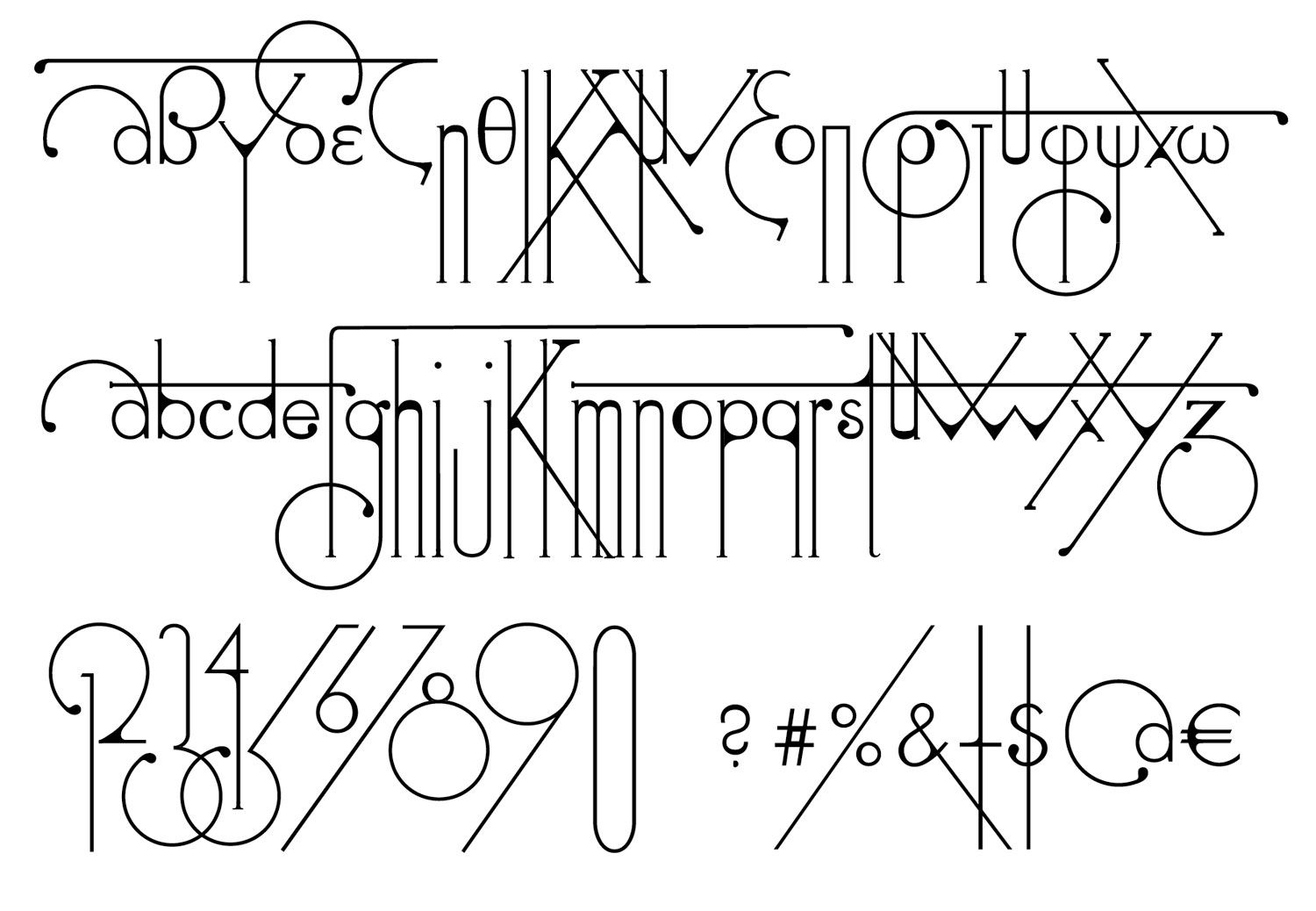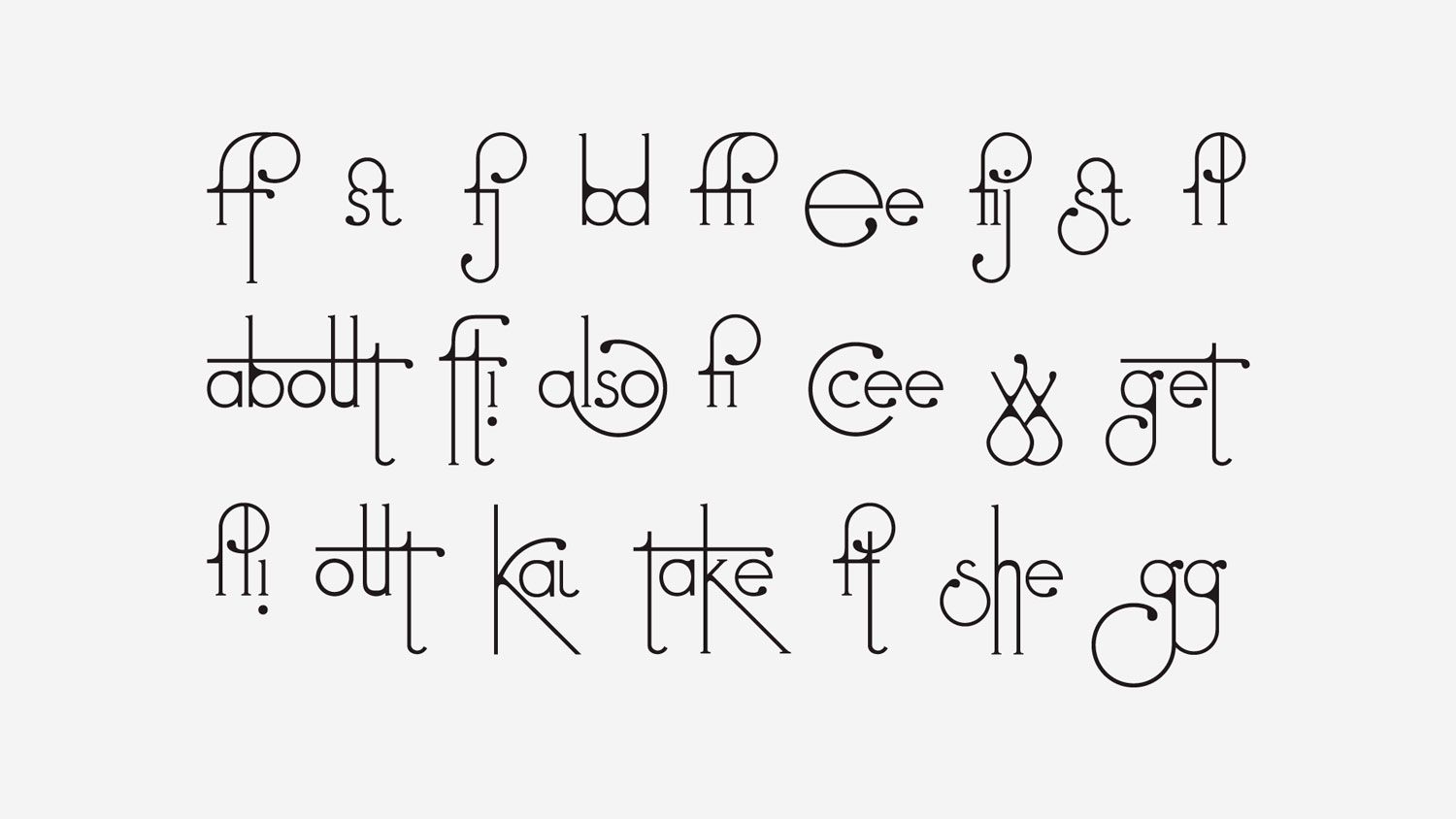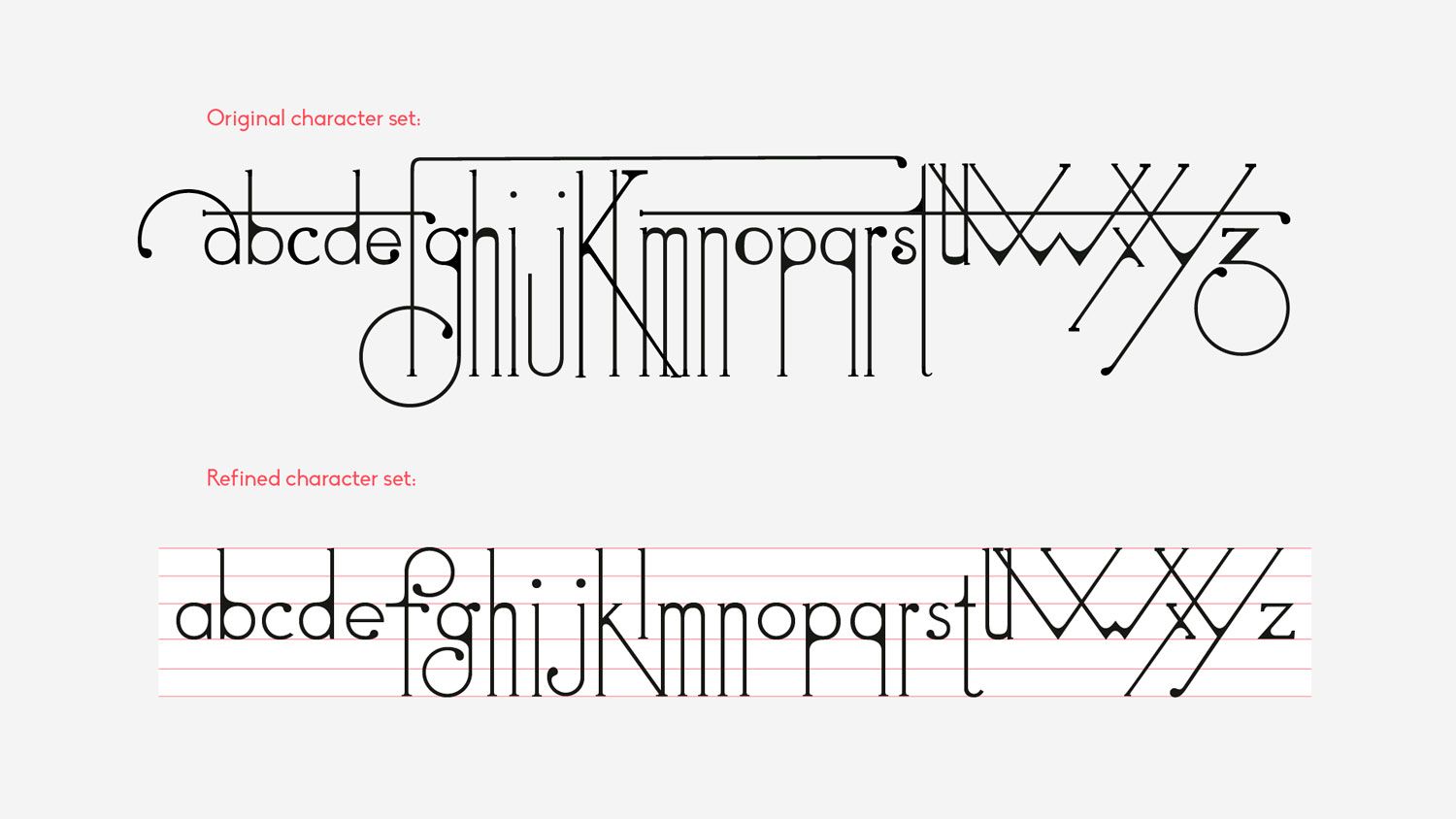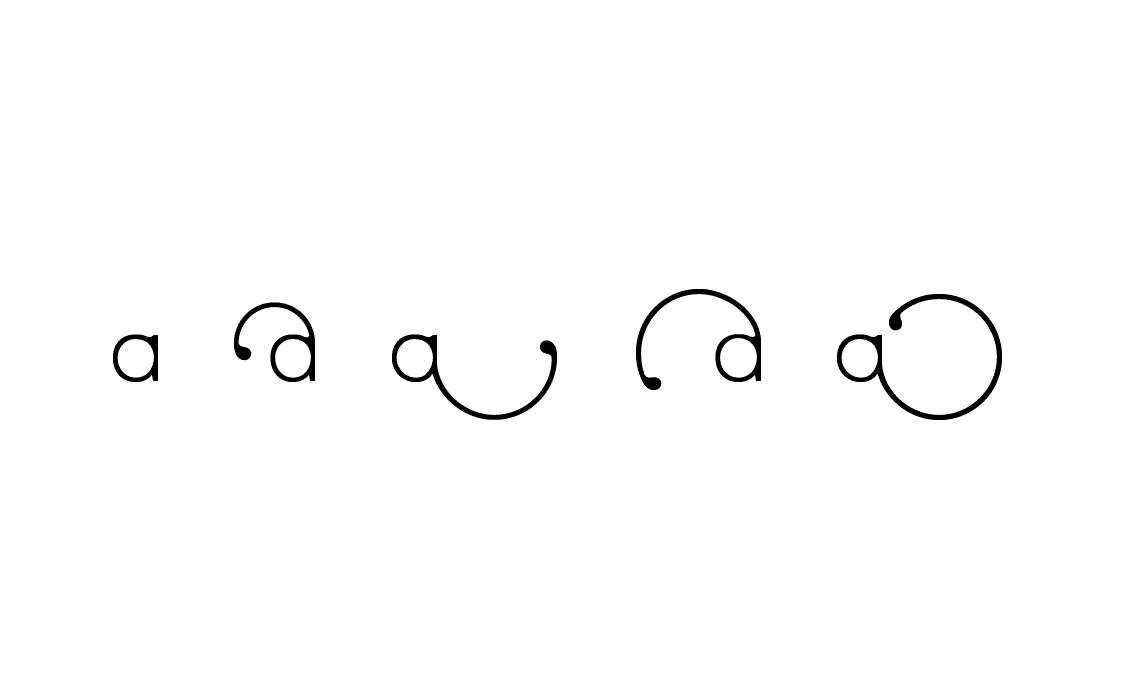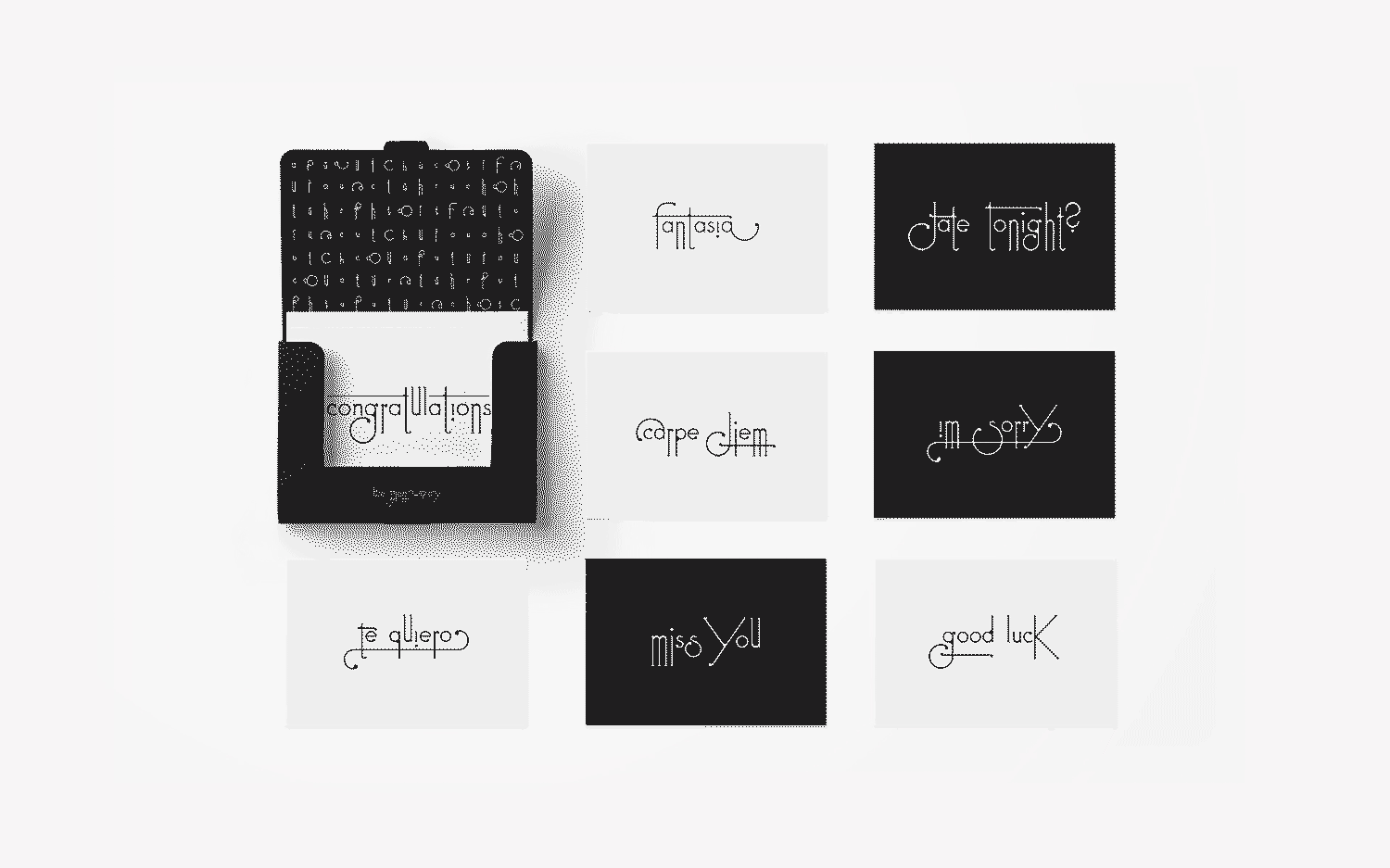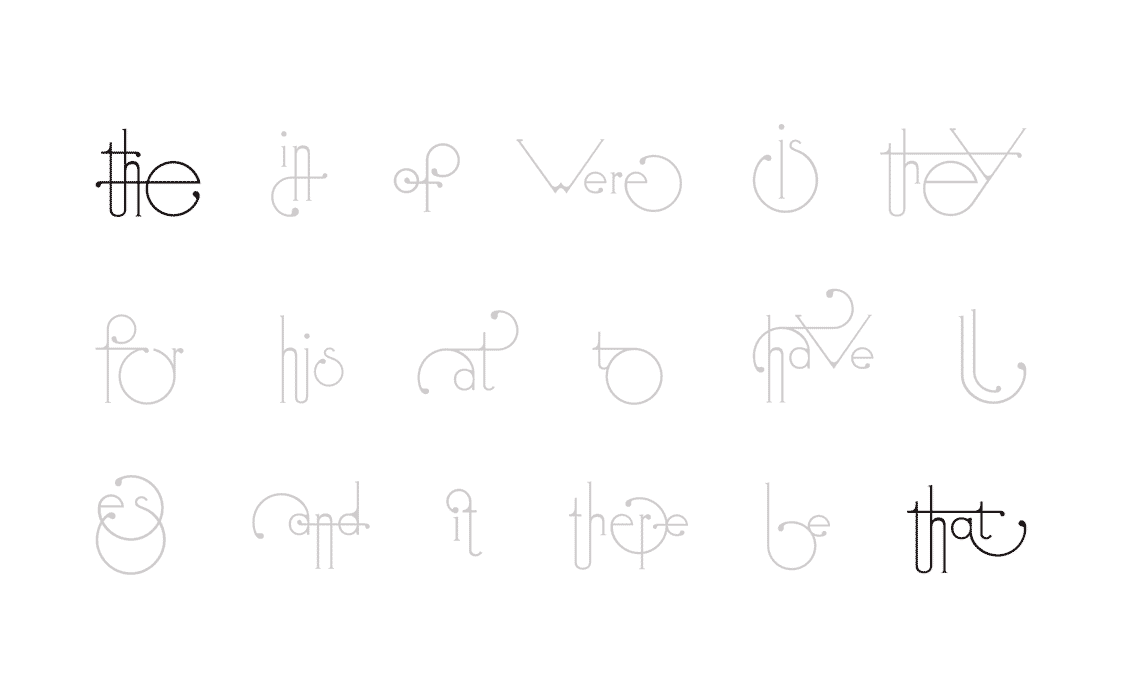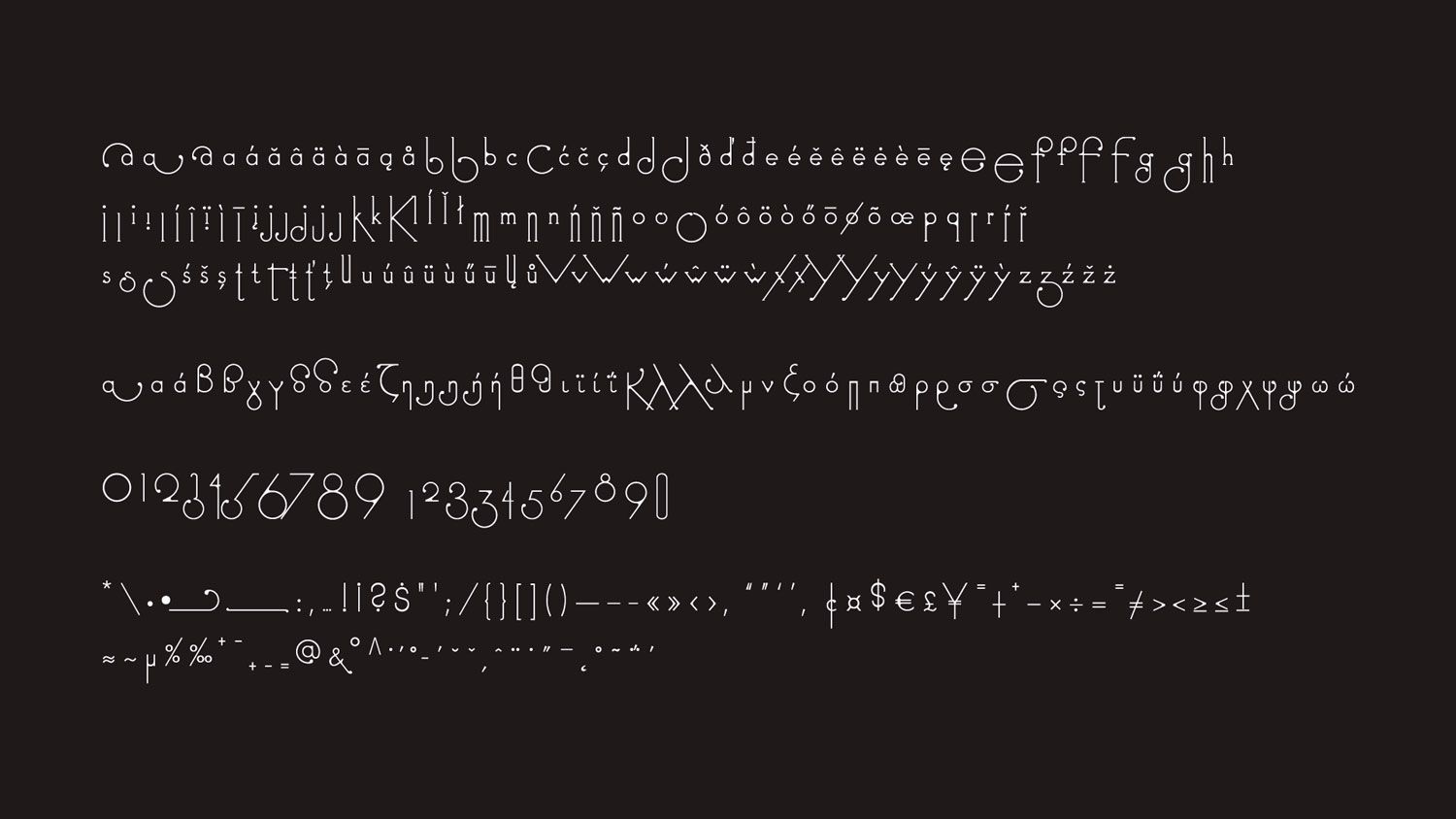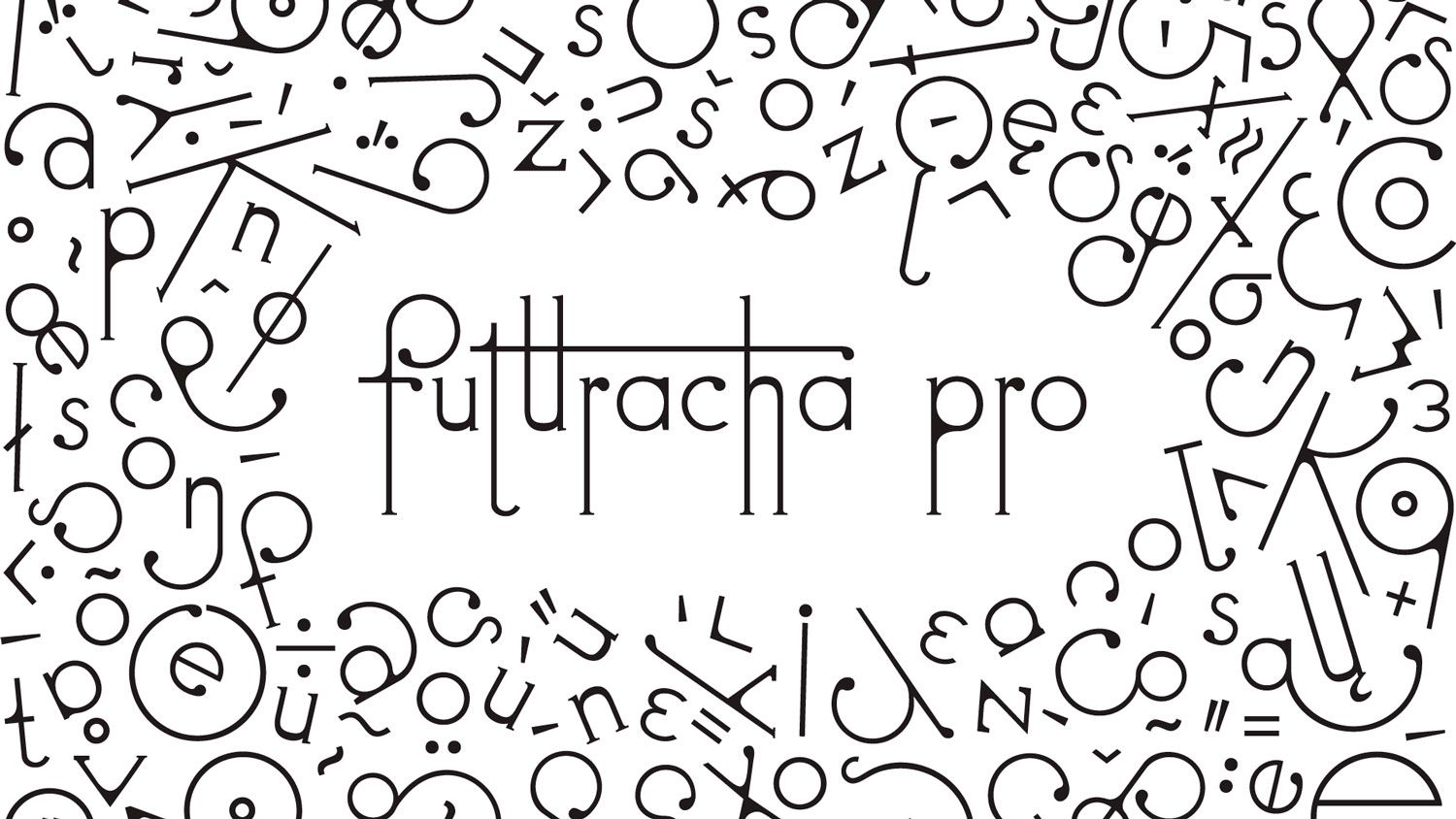
Futuracha, una tipografía que cambia mientras escribes
Una cucaracha fue la fuente de inspiración para crear la tipografía que modifica sus ligaduras a medida que tecleas.
Desde que Paul Renner la creo en Alemania a finales de la década de los años 20, la tipografía Futura ha sido protagonista en grandes hitos de la historia de la humanidad (fue la primera tipografía de la historia en aterrizar en la luna) y ha servido como fuente de inspiración y punto de partida para innumerables proyectos. Uno de ellos es Futuracha, una tipografía que toma el nombre del apócope resultante de unir las palabras 'Futura' y 'cucaracha', que se adapta sus ligaduras a medida que escribimos.
El equipo del estudio creativo griego holy ™ diseñó la tipografía Futuracha hace cinco años como parte de un proyecto experimental. Este incluía publicar la tipografía, de manera que cualquier pudiese interactuar con ella y diseñar sus propias variaciones. El resultado superó todas sus expectativas iniciales: Futuracha se descargó más de 245.000 veces por creativos de más de 180 países diferentes.
Pero el archivo eran un simple .eps que no permitía usar la tipografía como tal. En vista del éxito alcanzado con el proyecto, el equipo de holy ™ ha puesto en marcha una campaña de crowdfunding para desarrollar la versión Pro de Futuracha. Esta tiene como principal característica, además de las sinuosas formas de su antecesora, una serie de ligaduras mutables que se adaptan y cambian en función de las letras que se coloquen antes y después de cada una de ellas.
Futuracha pro, hoy por hoy, no hace lo que se dice en este post.
NO SE ADAPTA Y CAMBIA EN FUNCIÓN DE LAS LETRAS QUE SE COLOQUEN ANTES Y DESPUÉS DE CADA UNA DE ELLAS.
Compré la tipo a al estudio HOLY™ y al ver que no hacía lo que decía les escribí y esta fue su respuesta:
Dear Supercaligrafic, this gif was a promo video about where we want to go with Futuracha Pro. Back in that time, Futuracha Pro did not even exist. With your help, after the Indiegogo era, the alpha version of Futuracha Pro (the one you're typing with) includes 156 standard ligatures, 40 decorative ligatures and 86 alternative characters!
So, first of all, we gave priority to ligatures needed so that as many words as possible are easy to be read. More specifically, with this version, we assure that the 3.000 most common English words are legible and not affected by the font’s eccentric and decorative character.